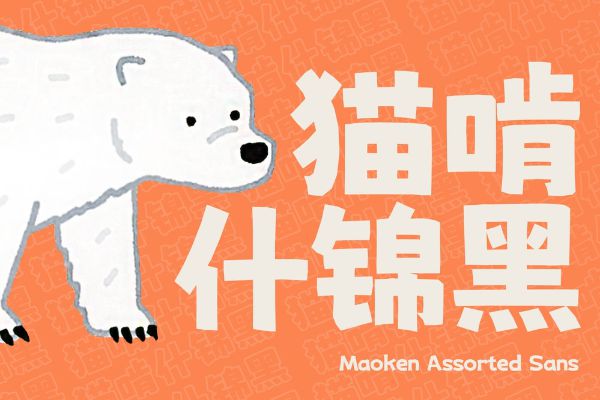
猫啃什锦黑
猫啃什锦黑是一款主打创意卡通风格的粗体方正字体,以独特设计语言为文字注入鲜活趣味。字体字形方正稳重,重心居中带来自然平衡感,中宫适中让字符舒展不拥挤,整体兼具粗体的力量感与排版的灵活性。 笔型设计极具巧思:笔画融入斜切元素,方头笔触搭配断开式连接,打破传统粗体的沉闷——斜切角度增添灵动韵律,断开处似随手勾勒的线条,让每个文字都像卡通角色般俏皮鲜活,完美契合儿童读物、文创设计、短视频标题等场景的活泼调性。 字体覆盖简体中文与繁体中文常规字符集,满足多场景文字表达需求。更值得关注的是,猫啃什锦黑支持免费商用,无需授权即可用于广告海报、包装设计、自媒体素材等商业场景,是设计师高效创作、降低成本的实用之选。无论是追求个性表达还是商用落地,这款字体都能让作品兼具视觉吸引力与实用性。